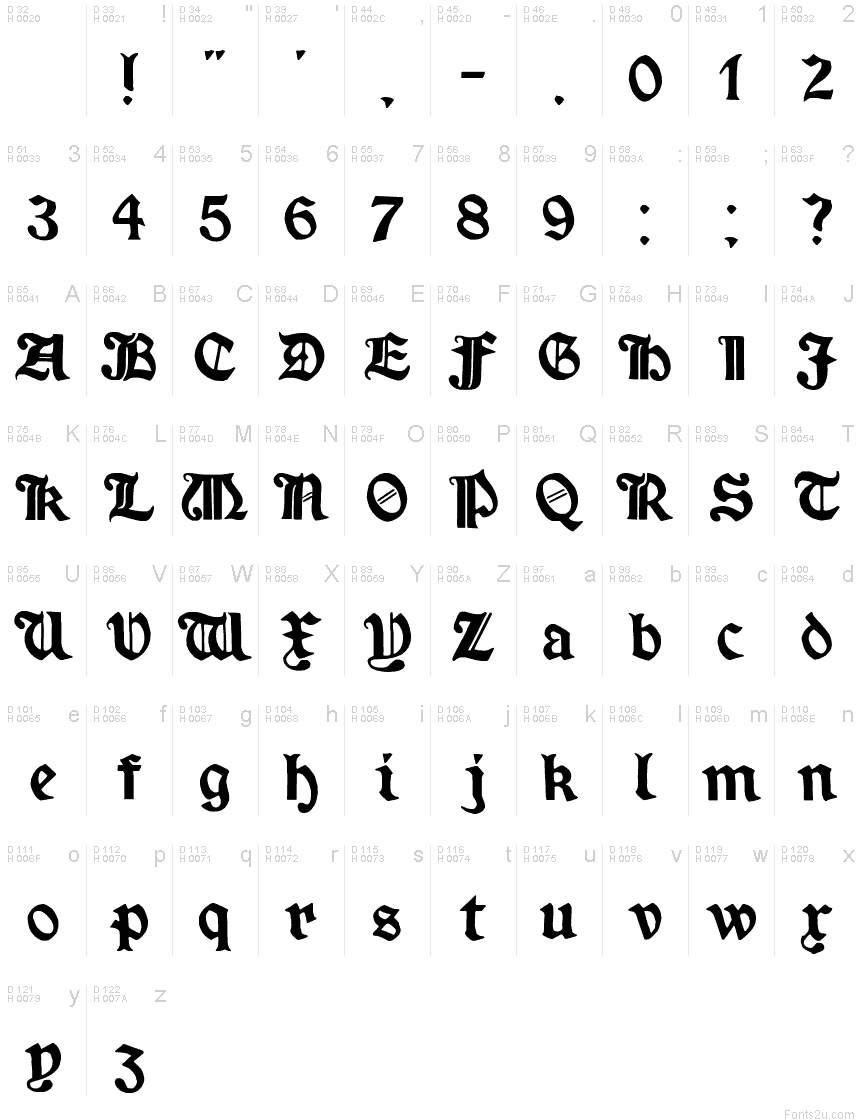
Minim ExtraBold od PJL to darmowy gotycki font z ostrymi, kanciastymi formami i spiczastymi szeryfami. Litery sprawiają wrażenie wykutych w ciemnym, pionowym wzorze, z wąskimi prześwitami i silnym rytmem dawnych czasów, co nadaje krojowi rzeźbiony, historyczny charakter.
Minim ExtraBold świetnie sprawdza się na okładkach książek, plakatach, w logotypach, oprawie muzycznej i zaproszeniach na wydarzenia tematyczne, ponieważ litery niosą ze sobą wyraźny, średniowieczny klimat bez potrzeby dodatkowych zdobień. Pasuje również do brandingu opartego na dziedzictwie, projektów fantasy i akcentów redakcyjnych, w których styl blackletter ma brzmieć formalnie i bezpośrednio.